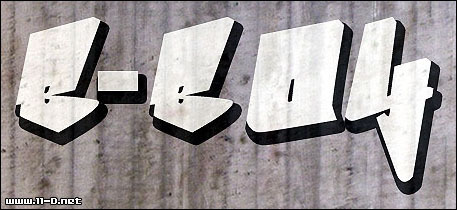
Bboy von Johan Waldenström ist eine kostenlose Graffiti-Schrift, die einschlägt wie ein frischer Tag an einer Backsteinmauer. Die kräftigen, geneigten Buchstaben wirken wie mit einem dicken Marker hingeworfen – massive schwarze Formen mit scharfen Schnitten und einer leichten Neigung, die Geschwindigkeit, Bewegung und Attitüde vermitteln. Der straffe Rhythmus und die kantigen Silhouetten lassen Wörter kompakt und wuchtig wirken, wie der Name einer Crew auf einem Bahnwaggon.
Mit Bboy holst du dir raue Street-Energy, ohne an Klarheit einzubüßen. Sie glänzt auf Postern, Album-Covern, Streetwear-Designs, bei Skate-Marken, Event-Flyern und auffälligen Social-Media-Posts. Diese kostenlose Schrift liebt große Formate, bei denen ihre blockartigen Formen schreien, nicht flüstern dürfen. Kombiniere Bboy für den Fließtext mit einer sauberen, neutralen serifenlosen Schrift, damit das Graffiti-Design der Star deines Layouts bleibt.
Präsentation und Schriftprobe von Bboy